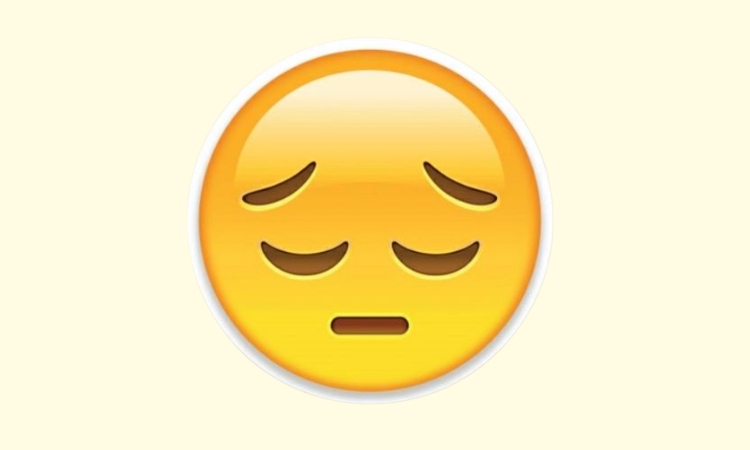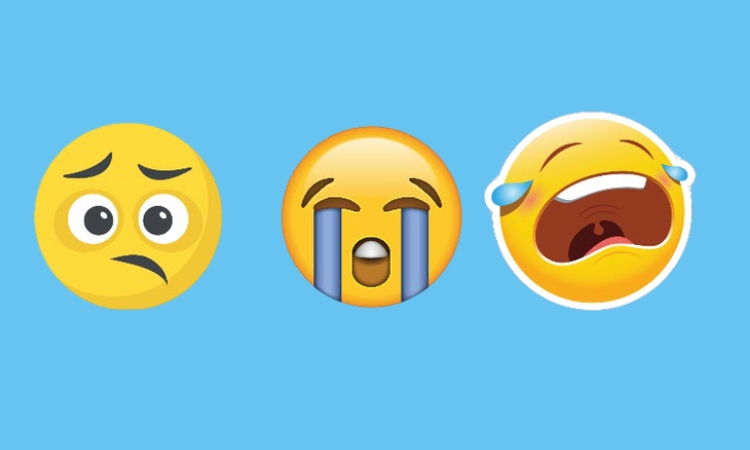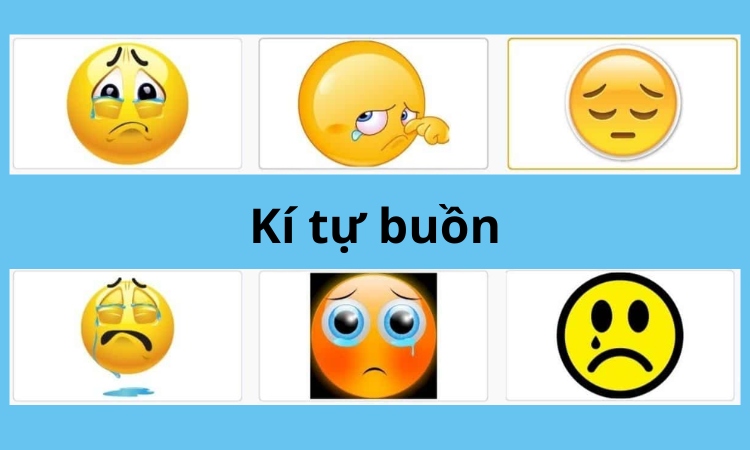
99+ kí tự buồn siêu đẹp được tìm kiếm nhiều nhất hiện nay
Kí tự buồn đang trở thành xu hướng được giới trẻ tìm kiếm để thể hiện cảm xúc trong tên hiển thị, bio hoặc tin nhắn. Những mẫu chữ đặc biệt mang nét u sầu, cô đơn giúp bạn truyền tải tâm trạng một cách tinh tế và khác biệt.
Bộ sưu tập kí tự buồn phổ biến nhất dưới đây được phân loại theo các nhóm: kí hiệu icon buồn đơn giản, kí tự đặc biệt mặt buồn, kiểu chữ đẹp theo chủ đề buồn, kí tự ngẫu nhiên, xáo trộn,... giúp bạn nhanh chóng sao chép và sử dụng.
Kí tự buồn là tập hợp các biểu tượng, icon, kí hiệu cảm xúc được thiết kế để thể hiện trạng thái tiêu cực như buồn bã, cô đơn, thất vọng. Những kí tự này thường được nhiều người dùng tìm kiếm để sử dụng trong bio Facebook, caption TikTok, tên game hoặc bất kỳ nội dung nào muốn truyền tải tâm trạng.
Trong thế giới mạng xã hội, kí tự đặc biệt buồn trở thành một phương tiện thể hiện cá tính, cảm xúc nội tâm mà không cần nói quá nhiều.
Dưới đây là danh sách phân loại chi tiết các dạng kí hiệu icon buồn đơn giản, kí tự đặc biệt mặt buồn, kiểu chữ đẹp theo chủ đề buồn, kí tự ngẫu nhiên, xáo trộn,... mà bạn có thể tham khảo:
Những kí hiệu icon buồn thể hiện trực tiếp gương mặt buồn, khóc, thất vọng,... giúp truyền tải cảm xúc rõ ràng mà không cần văn bản. Theo Unicode Consortium, phần lớn icon này thuộc các khối Emoticons (U+1F600–U+1F64F), Supplemental Symbols and Pictographs (U+1F900–U+1F9FF), Miscellaneous Symbols (U+2600–U+26FF) và Symbols and Pictographs Extended-A (U+1FA70–U+1FAFF).
Tham khảo danh sách các kí tự buồn đơn giản, dễ nhận biết thông qua bảng dưới đây:
Dưới đây là nhóm kí tự đặc biệt mặt buồn được tạo thành từ các ký hiệu văn bản, mô phỏng biểu cảm con người rất sinh động, thường dùng trong bio hoặc tin nhắn:
Những kiểu chữ được cách điệu theo phong cách nghệ thuật buồn, nhẹ nhàng hoặc u sầu rất phù hợp để chèn vào tiểu sử, nickname hoặc bài viết cá nhân. Dưới đây là một số gợi ý về kiểu chữ đẹp theo chủ đề buồn ấn tượng:
Những tổ hợp kí tự icon buồn được tạo một cách ngẫu nhiên nhưng lại vô cùng độc đáo. Dưới đây là một số kí tự buồn ngẫu nhiên mà bạn có thể sử dụng để tạo điểm nhấn tên game, bio hoặc bình luận tâm trạng:
Các ví dụ dưới đây sử dụng hiệu ứng xáo trộn kí tự giúp tên hoặc chữ trở nên nghệ thuật và lạ mắt, phù hợp với người thích sự sáng tạo, khác biệt:
Sau đây là tập hợp tất cả các dạng kí hiệu buồn, kiểu chữ đặc biệt, kí tự mặt buồn dành riêng cho bạn. Từ đơn giản đến cầu kỳ, bạn có thể chọn và sao chép ngay.
Dành cho những ai đang tìm kiếm cảm hứng để đặt tên buồn, tên Liên Quân buồn hay tên bio TikTok tâm trạng là những lựa chọn gây ấn tượng mạnh. Dưới đây là một vài tên Liên Quân buồn đề xuất mà bạn có thể áp dụng cho tài khoản của mình:
Trước khi chèn bất kỳ kí hiệu buồn nào vào tên hiển thị, hãy dành vài phút xem qua những thắc mắc phổ biến dưới đây để hiểu rõ hơn:
Không thể dùng các ký tự đặc biệt buồn trong tên Facebook ngay cả khi chưa xác minh tài khoản. Dù chưa xác minh tài khoản, Facebook vẫn có hệ thống kiểm duyệt tên tự động dựa trên các tiêu chuẩn của họ. Theo chính sách của Facebook, những thứ không được phép trong tên bao gồm:
Biểu tượng cảm xúc (ví dụ: 😢, 😭, 🥺)
Biểu tượng, ký tự đặc biệt, số, cách viết hoa bất thường
Các dạng tên không giống tên thật trong đời sống.
Facebook thiết lập các nguyên tắc này để đảm bảo mọi người sử dụng tên thật mà họ thường được gọi trong đời sống hàng ngày
Các ký tự icon buồn hoạt động ổn định trên cả iPhone và Android trong hầu hết các trường hợp. Các kí hiệu này sử dụng bộ mã Unicode phổ biến nên tương thích tốt với hệ điều hành hiện đại như: iOS, Android, Windows và macOS. Dù bạn dán các icon này vào phần bio Facebook, bình luận TikTok hay tin nhắn Zalo, chúng vẫn giữ nguyên hình dạng và ý nghĩa mà không gặp lỗi hiển thị sai.